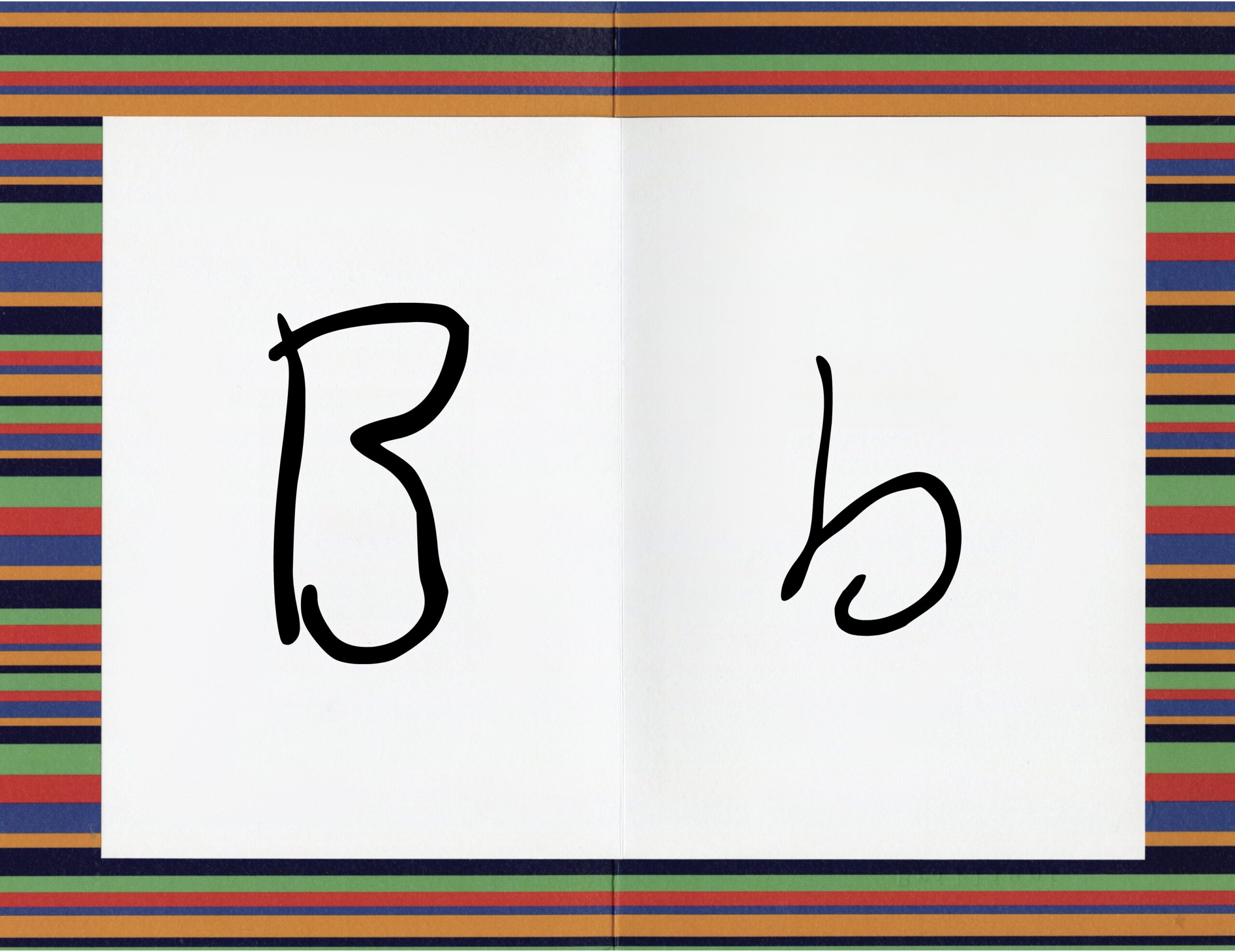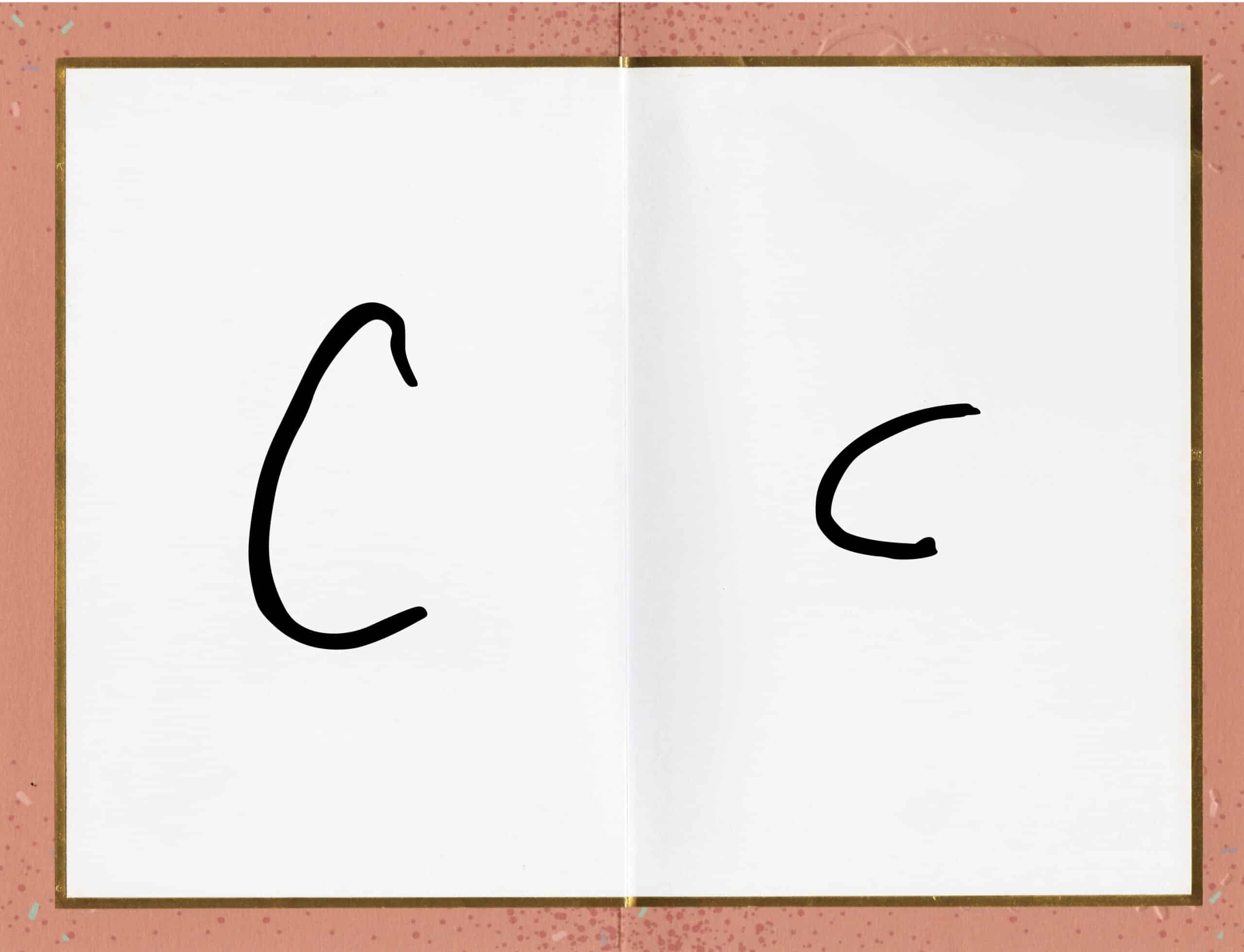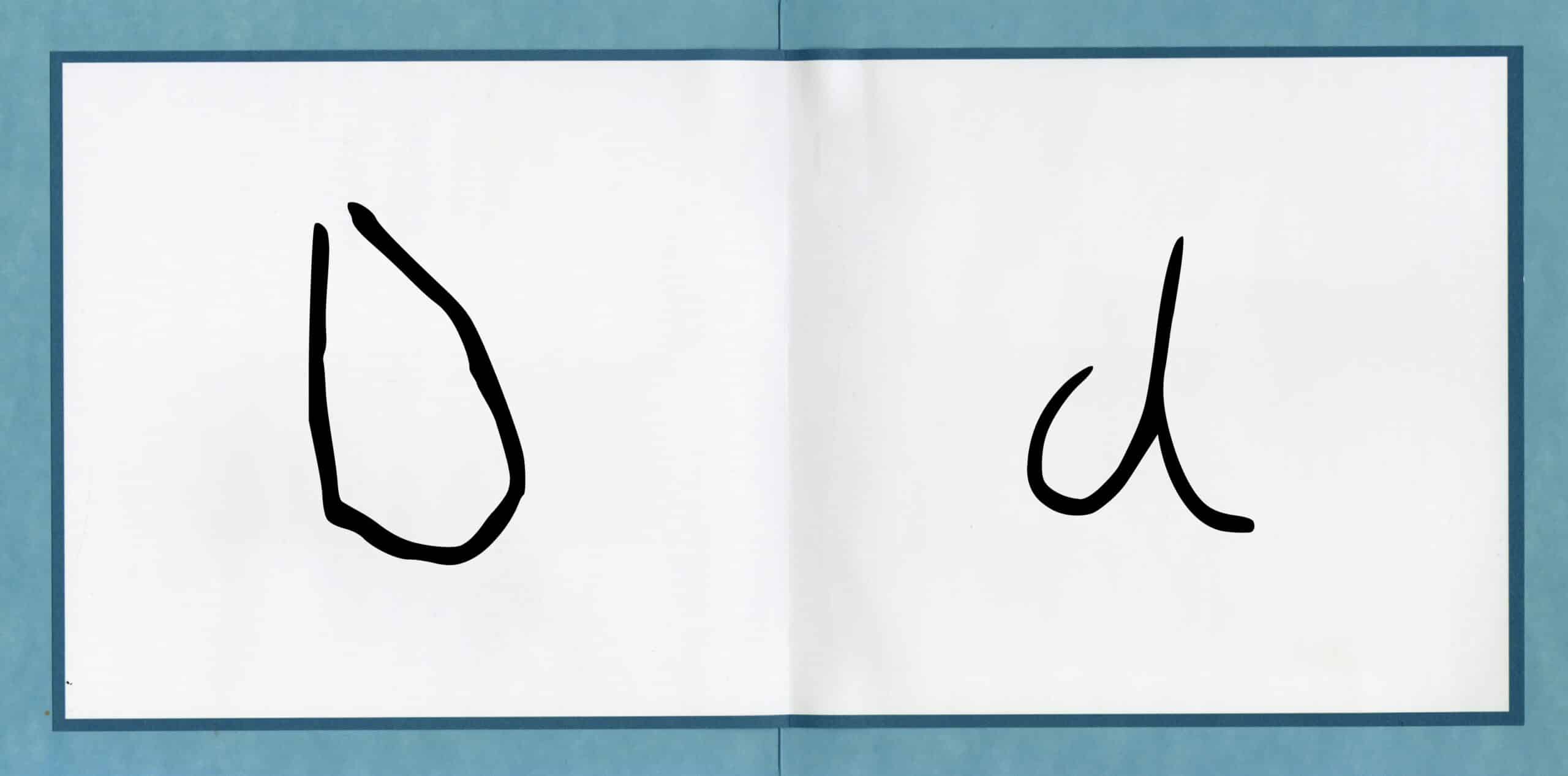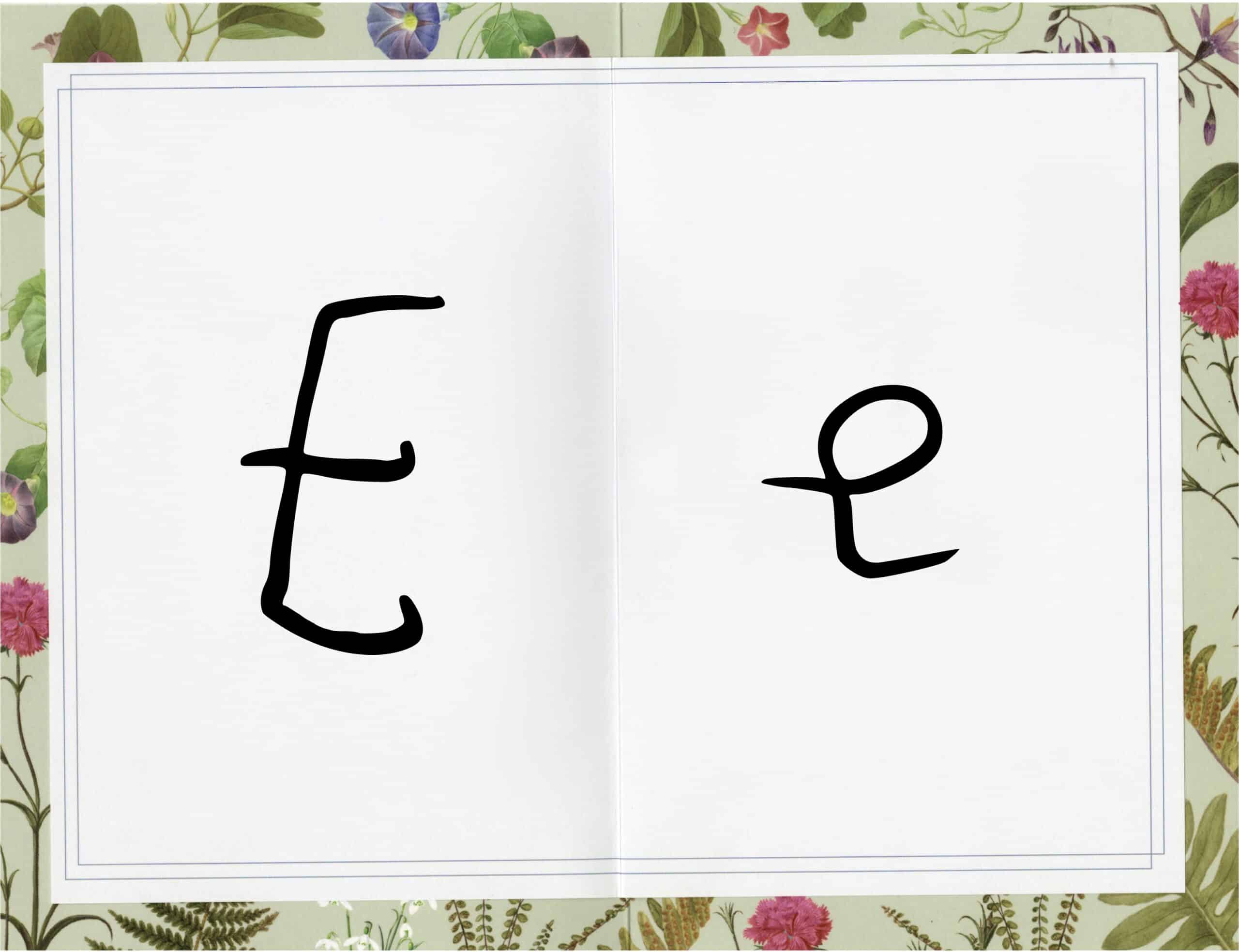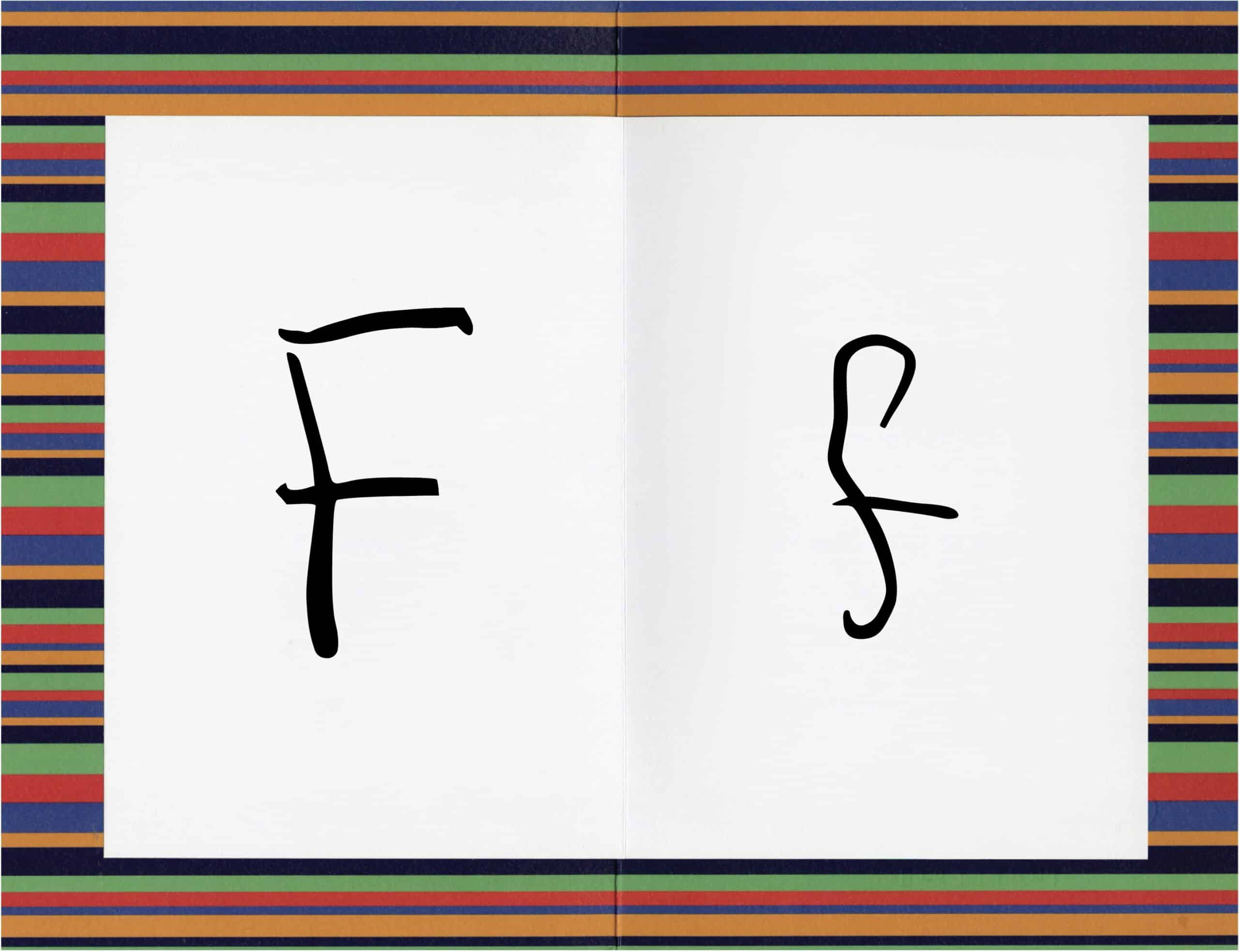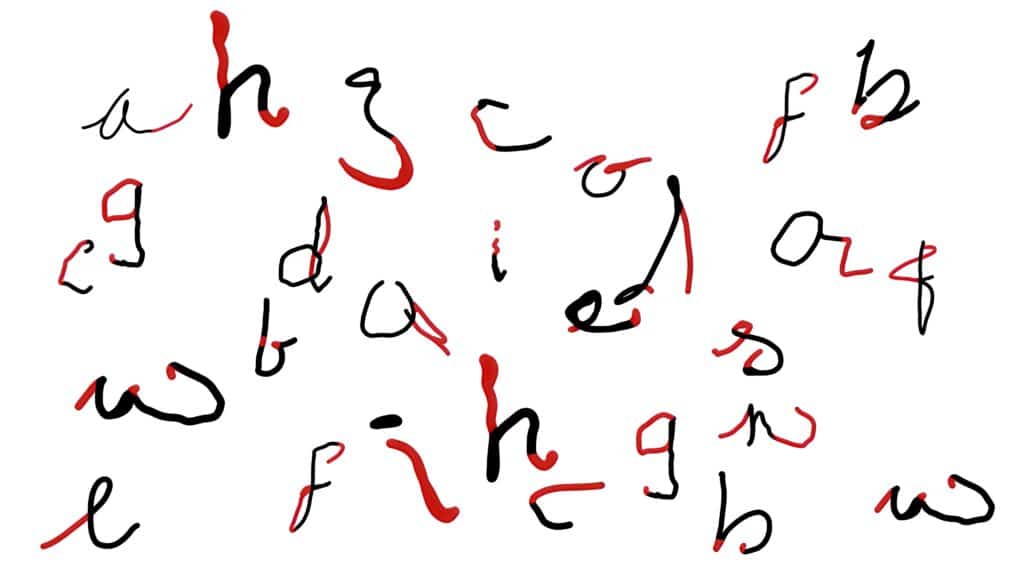
Monotype Re:Vision: Wie Typografie sozialen Wandel ermöglicht
D&AD-Award für „Silent Shake“
Parkinson-Früherkennung durch Typografie
Monotype Re:Vision: Wie Typografie sozialen Wandel ermöglicht. Typografie als Werkzeug für Empathie, Aufklärung und gesellschaftliche Relevanz: Die ausgezeichnete Kampagne „Silent Shake“ macht erste Anzeichen von Parkinson durch Handschrift sichtbar – und zeigt, wie Schrift den Dialog zwischen Gesellschaft und Gesundheitswesen stärken kann.
Monotype rückt im Rahmen seiner globalen Re:Vision-Initiative Freedom, Law & Order die Kampagne „Silent Shake“ in den Fokus. Die bei den diesjährigen D&AD New Blood Awards mit dem begehrten Pencil ausgezeichnete Kampagne zeigt eindrucksvoll, wie Schriftgestaltung gesellschaftlich relevante Themen in den Mittelpunkt stellen und emotionale Reaktionen auslösen kann.
Warum „Silent Shake“ so wichtig ist
Das von Studierenden entwickelte Projekt entstand auf Grundlage eines von Monotype initiierten Briefings. Darin wurden junge Kreative weltweit aufgefordert, sich mit der Rolle von Schrift in Zeiten von Freiheit, Kontrolle und gesellschaftlichem Wandel auseinanderzusetzen. – mit beeindruckender Resonanz: 13.651 Downloads, 216 Einreichungen aus aller Welt, 13 Finalist:innen und einem klaren Gewinner: Silent Shake.
Die Kampagne nutzt echte Handschriften von Menschen mit Parkinson, um auf erste, oft übersehene Symptome der Erkrankung aufmerksam zu machen – etwa feine Veränderungen der Motorik, die sich in der Handschrift zeigen. Durch die visuelle Aufbereitung wird Typografie hier zum Werkzeug für Sensibilisierung, Früherkennung und Aufklärung.
Die Designerinnen Hollie Spooner, Lizzie Day und Katie May Charlesworth betonen:
„Monotypes Briefing war besonders, weil es um echte Wirkung ging – um die Chance, mit Design etwas zu verändern. Uns war sofort klar: Das ist unsere Richtung. Silent Shake ist für uns ein Herzensprojekt, das ganz natürlich entstanden ist.“ Sue Daun, Creative Director bei Interbrand und Jurymitglied der D&AD Awards, ergänzt: „Das war mehr als Design – es war emotionale Wirkung durch Schrift. Silent Shake hat den Kern des Briefings auf neue Weise interpretiert und das Publikum berührt. Es ging nicht darum, laut zu sein – sondern sichtbar.“
Re:Vision – Schrift im gesellschaftlichen Kontext
Mit seiner Initiative Re:Vision untersucht Monotype, wie Schrift unser Verständnis von Freedom, Law & Order prägt – von Typografie im öffentlichen Raum bis hin zu digitalen Interfaces. Silent Shake steht exemplarisch für diesen Ansatz: Design, das aktiviert, sensibilisiert und informiert. Dabei beleuchtet Re:Vision zentrale Dimensionen moderner Typografie:
Typografie als Aktivismus: Schrift kann Tabus brechen, Empathie wecken und gesellschaftliche Debatten anstoßen.
Typografie als Stimme: Ob auf Verkehrsschildern oder Protestplakaten – Typografie transportiert kollektive Botschaften.
Typografie und Technologie: Geolokalisierung, Animation und variable Fonts eröffnen neue Wege des Storytellings.
Typografie im Zeitalter der KI: Trotz technologischer Beschleunigung bleibt der menschliche Ausdruck über Schrift unverzichtbar.
Laurène Girbal, Type Designerin bei Monotype und Jurymitglied erklärt: „Typografie ist gelebte Geschichte in Buchstabenform. Wenn sie mit Empathie und Neugier gestaltet wird, kann sie Kultur verändern.“ Und Sammi Vaughan, Partnerships Director bei D&AD, ergänzt: „Wir wollten, dass sich die Studierenden mit echten Spannungsfeldern auseinandersetzen – genau wie im Berufsleben. Die besten Arbeiten haben Typografie als Stimme genutzt, nicht nur als Gestaltungsmittel.“